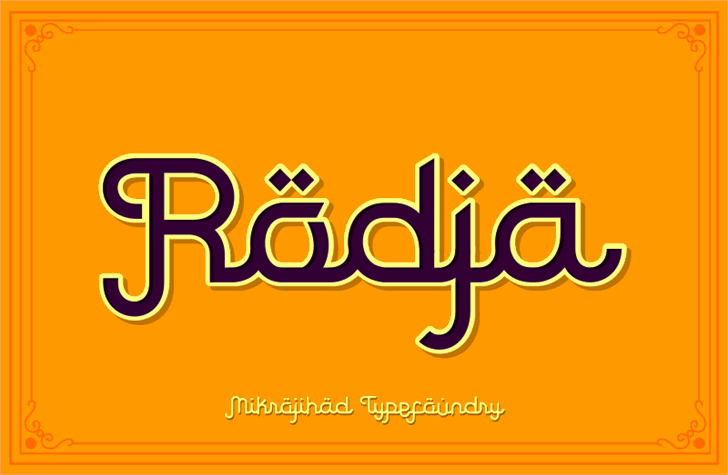
Rodja font family – Download Grátis
A Rodja Font Family é uma elegante família de negrito criada pelo designer Hamilton, perfeita para quem busca um estilo arcaico e sofisticado. Este Blackletter Typeface combina características únicas que remetem aos textos manuscritos da era medieval, com um toque moderno que o torna ainda mais versátil. Suas linhas elegantes e riscadas definidas oferecem uma aparência impecável para qualquer projeto gráfico, seja ele editorial, publicidade ou arte digital. Com sua liberação de licença comercial disponível gratuitamente para download aqui: https://www.revolge.com/product/rodja-script-family/, a Rodja Font Family é o tipo certo para quem deseja adicionar um toque único e sofisticado aos seus trabalhos.